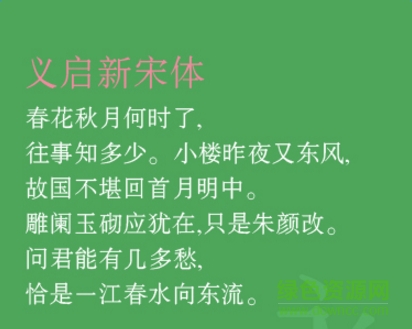
義啟新宋體是一款義啟類(lèi)新型宋體字體軟件,新宋體以細(xì)粗結(jié)合的大體變化,襯托出字體的高端大氣,比較有型有范,適合于正式場(chǎng)合標(biāo)題內(nèi)容的書(shū)寫(xiě),感興趣的朋友歡迎來(lái)綠色資源網(wǎng)下載體驗(yàn)!
宋體,是為適應(yīng)印刷術(shù)而出現(xiàn)的一種漢字字體。筆畫(huà)有粗細(xì)變化,而且一般是橫細(xì)豎粗,末端有裝飾部分,點(diǎn)、撇、捺、鉤等筆畫(huà)有尖端,屬于襯線(xiàn)字體,常用于書(shū)籍、雜志、報(bào)紙印刷的正文排版。義啟新宋體,在設(shè)計(jì)上,作者延續(xù)了宋體的特色,但宋體畢竟是為了印刷條件而發(fā)展傳承的,在電子屏幕顯示上村在種種弊端,而義啟新宋體在繼承宋體特性的基礎(chǔ)上加大了橫筆畫(huà)的粗度及比例,使得顯示更加優(yōu)化。